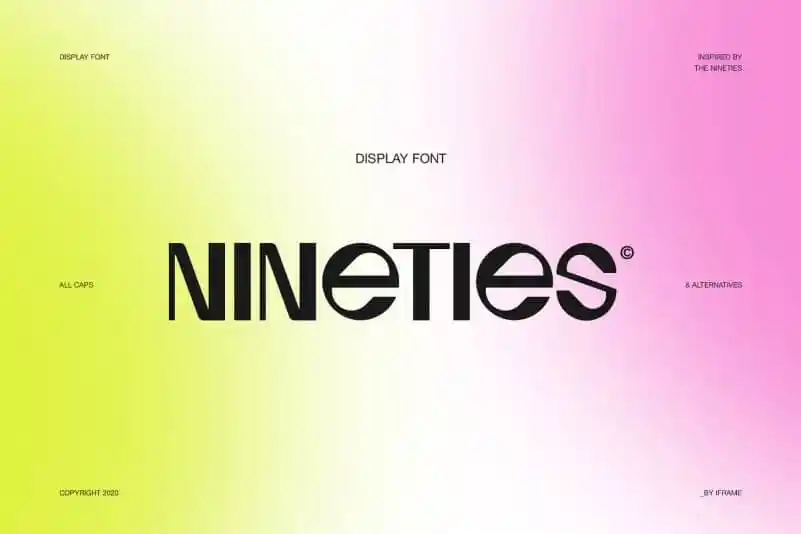
Nineties Display Font – Download Grátis
Nineties Display Font é uma elegante fonte sans-serif que captura a essência do final dos anos 80 e início dos 90. Inspirada nos designs icônicos dessa década, essa fonte atesta seu valor tanto para criações memoráveis quanto para estilos de design modernos e sofisticados. Desenhada pelo designer beacon e compartilhada na comunidade de fontes online, Nineties Display é perfeita para incorporar em uma variedade de formatos de projeto, desde ambientes futuristas até cenários retro vintage relacionados a videogames ou jogos de mesa. Esteu em publicações de revista, cartões de aniversário, selos digitais e muito mais.